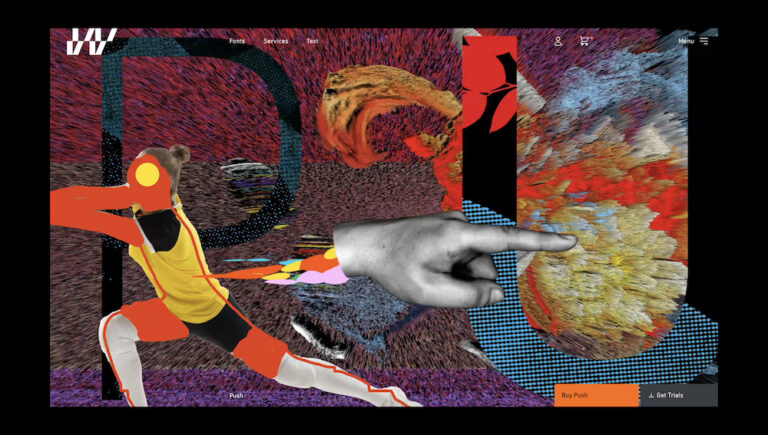
Auch so kann eine Foundry aussehen: Das Fontwerk schärft sein Profil!
Neue, spannende Visuals, erweiterter TypeTester, vereinfachtes Lizenzierungsmodell: Die Berliner Foundry Fontwerk hat ihre Website einem Relaunch unterzogen, der so stylisch wie umwerfend User-freundich ist.
Eigentlich wollte die Berliner Schriftgießerei Fontwerk ihre Website nur ein wenig überarbeiten, den Auftritt refreshen und hier und da ein paar Kleinigkeiten ändern.
Doch aus dem kurzen aufpolieren wurden schließlich zwei Jahre – und in denen entstand ein neuer Webauftritt, der eine Freude ist. Für Kreative, Agenturen, Brand Manager und alle anderen, die sich für spannende Schriften und gutes Design interessieren.
Ihr Ziel, den Schriften den nötigen Raum zum Atmen geben, sich aber gleichzeitig als Foundry mit einer starken visuellen Personality zu präsentieren, hat das Fontwerk auf eigene Weise umgesetzt.
Die Schriften stehen dabei im Mittelpunkt, klar und prägnant und schwarz auf weiß. Aber hinter den einzelnen Fonts verbergen sich Visualisierungen, die den Kern der einzeln Schrift umreißen. Dabei werden Einkaufswagen zu abstrakten Mustern, perlen Wassertropfen oder fügen sich abstrakte Farbwolken immer wieder neu zusammen.
Gleichzeitig werden die Schriftgestalter:innen persönlich vorgestellt und dazu trifft ein kräftiges Orange, das in der Navigation Schlaglichter setzt, auf ein erdiges, zartes Grün.
Schriften im Mittelpunkt – und der TypeTester
Die Website ist so strukturiert, dass man sie auf zwei verschiedene Arten nutzen kann. Hat man es eilig, klickt man in der Kopfzeile direkt in den Hauptbereich mit seinen Schriftarten, Dienstleistungen und dem Blog der Foundry, der Interessierte mit tiefergehenden Informationen versorgen möchte und zu Diskussionen anregen.
Und das Testen wird großgeschrieben. Deshalb hat Fontwerk seine »Try before you Buy«-Funktion erweitert und sie zudem vom Kaufprozess abgekoppelt. Lädt man die »Trial Fonts« herunter, die zu 99 Prozent identisch mit den Vollversionen sind, hat man gleichzeitig auch die Möglichkeit den Rest der Bibliothek zu testen.
Dafür wurde der TypeTester, der schon zuvor zentraler Bestandteil der Website war, radikal überarbeitet. Und so kann man Schriften jetzt ganz komfortabel in eigenen Dokumenten und Projekten ausprobieren.
Stattdessen man sich auf die Schriften selbst konzentrieren, die »Stars der Show«, wie Ivo Gabrowitsch, Gründer von Fontwerk, sie nennt. Auf die Case oder Change, die McQueen oder Pangea, die immer auch im Anwendungen gezeigt werden, auf Fotografien von Plakaten, Packagings oder Magazin-Covern, Büchern oder Leitsystemen.
Statt im Typografen-Turm zu sitzen, führt die Fontwerk Website mitten ins Leben hinein, überrascht mit Mouseover-Effekten und charmanten Definitionen, führt in den »Barcelona Pavillon« von Ludwig Mies van der Rohe, zu leeren Supermarkt-Regalen oder unter die Berliner Hochbahn.